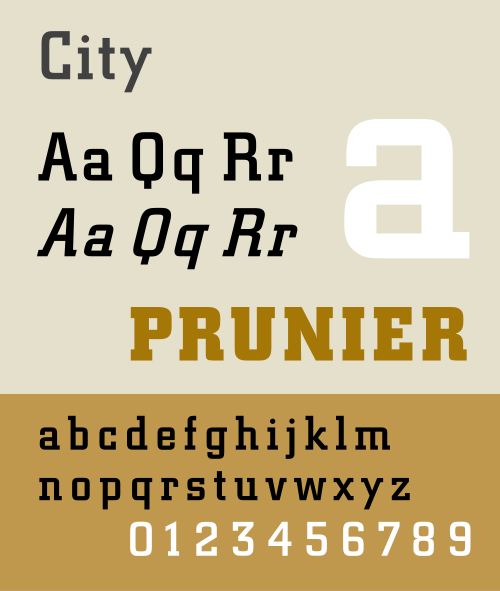
| カテゴリ | セリフ |
| 分類 | スラブセリフ |
| デザイナー | ゲオルグ・トランプ |
| 鋳造所 | H.ベルトルトAG |
| リリース日 | 1930年頃 |
City は、ゲオルグ・トランプがデザインし、1930 年頃にドイツのベルリンにあるBerthold 活字鋳造所からリリースされたスラブ セリフ 書体です。 [a]スラブ セリフに分類されますが、City は直角と反対の丸い角の幾何学的構造に強いモダニズムの影響が見られます。この書体は、機械時代と産業からインスピレーションを得ています。外側の円が内側の直線的な空間を和らげるなど、一貫した繰り返し部分の使用により、非常に統一された洗練された書体となっています。
小文字のa は、内部が 2 つの水平な長方形で構成され、外側のスキンはそのカウンターに沿っていますが、外側のストロークと有機的な曲線とのコントラストが常にあります。この書体は、ライト、ミディアム、ボールドの 3 つの太さで作成され、それぞれローマン体とイタリック体です。グラフィック デザイナーのJan Tschicholdは、バーゼルの出版社 Benno Schwabe & Co. が出版した 著書Typographische Gestaltungで City 書体を使用し、この書体の普及に貢献しました。
商業利用
- IBM社は1956年以降、企業ロゴにCityのバリエーションを使用し[3]、数十年にわたって技術マニュアルのタイトルページや表紙にCity Mediumを使用していました。
- サザンテレビはニュース番組「デイ・バイ・デイ」のタイトルに「City」を使用しました。
- 1998 年のアニメシリーズ「カウボーイビバップ」では、タイトル シーケンスに City が使用されました。
- この書体の異形は、CBS の犯罪ドラマシリーズ「マニックス」のタイトルとクレジットにも使用されました。
- ESPN は2015 年までの数年間、大学フットボールとバスケットボールの報道のブランド化に City Pro Bold を使用していましたが、それ以降はバスケットボールのみに使用しています。
- イタリア空軍( Aeronautica Militare ) は、ロゴに City Bold 書体を使用しました。
- オーストラリアのBBLおよびWBBL T20クリケットトーナメントでは、2019年までCityをブランド名に使用していました。このフォントは現在もトーナメントのロゴに使用されています。
シティプロ
2007 ~ 2009 年に、Berthold は City の OpenType Pro バージョンである City Pro をリリースしました。これは、中央ヨーロッパの Latin Extended A 文字をサポートしています。OpenType の機能には、序数、比例ライニング数字、下付き文字と上付き文字、分数などがあります。
スクエアスラブセリフ 711
BitstreamのSquare Slabserif 711フォントはCityに非常に似ており、ライト、ミディアム、ボールドのウェイトが用意されています。Square Slabserif 711はギリシャ文字とキリル文字もサポートしています。[4]